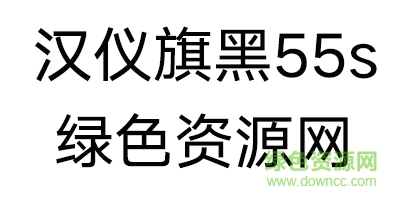
漢儀旗黑55字體是漢儀字庫里面的一款經(jīng)典黑體字體,這款字體端正大方,字跡一筆一畫非常工整,整體效果非常出色,非常適用于廣告、海報、宣傳的標(biāo)題,喜歡這款字體的朋友歡迎來綠色資源網(wǎng)下載體驗!
漢儀旗黑可謂黑體系列字體的巔峰大作,陰陽線的筆畫處理,筆觸彈性有力,字形俊秀挺拔,國際化的字體包裝方式,系統(tǒng)的中西文混搭、史上最大家族系統(tǒng),可以更完美的實現(xiàn)各類終端環(huán)境的呈現(xiàn)。